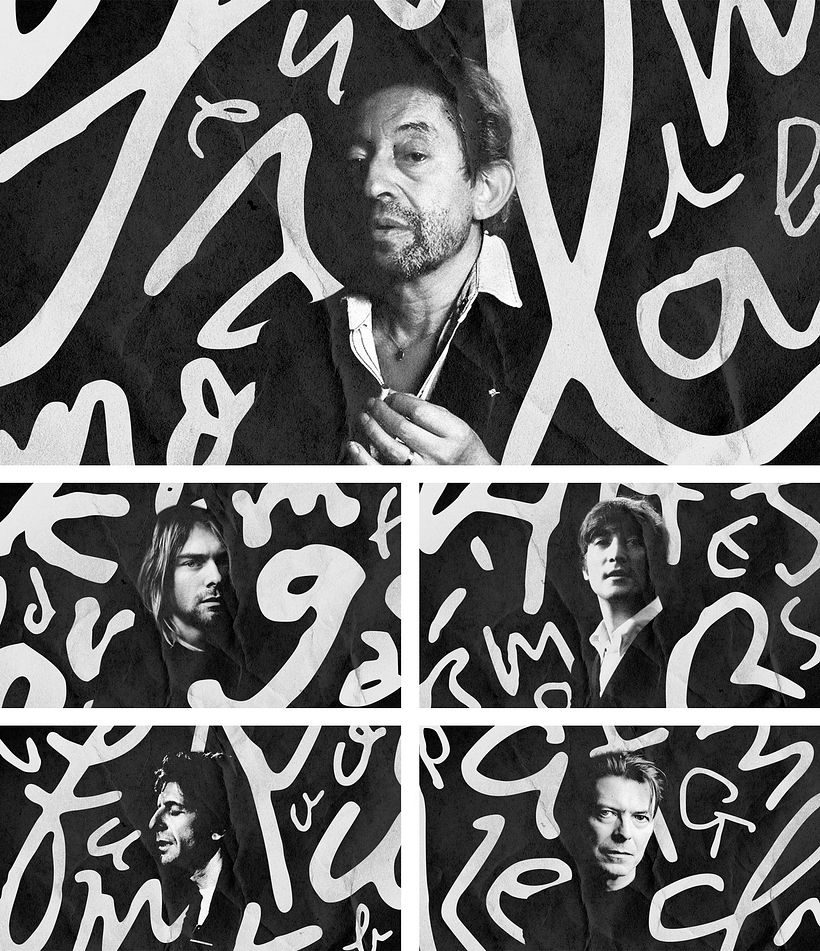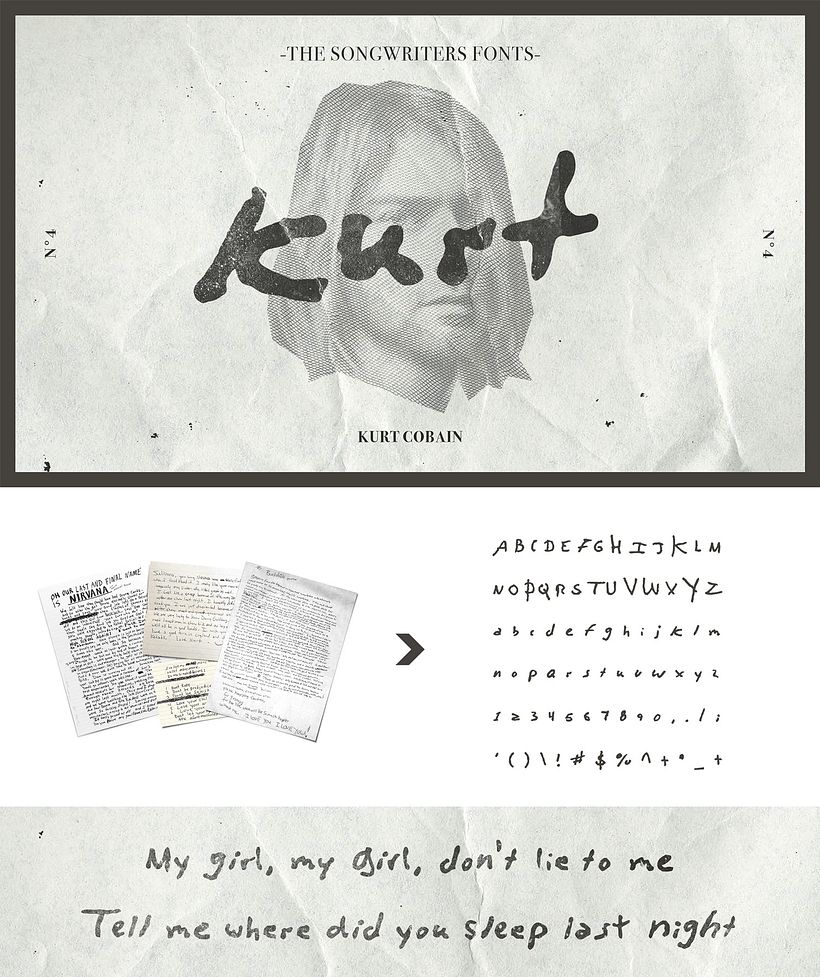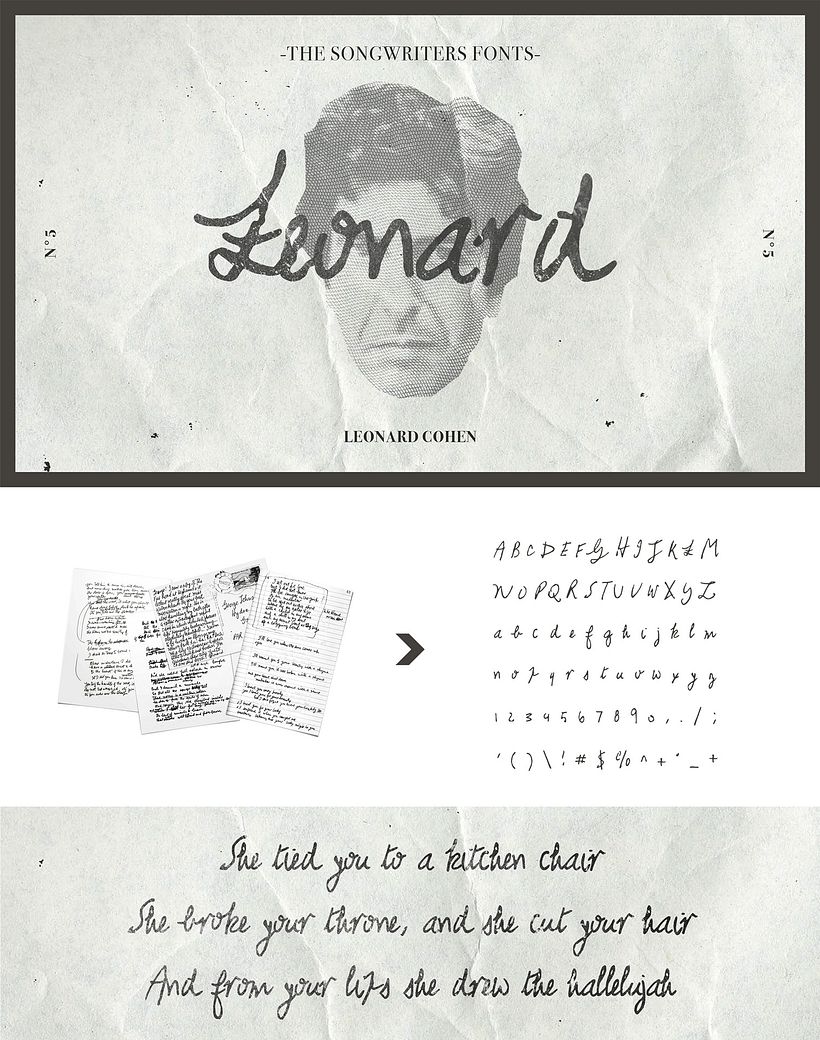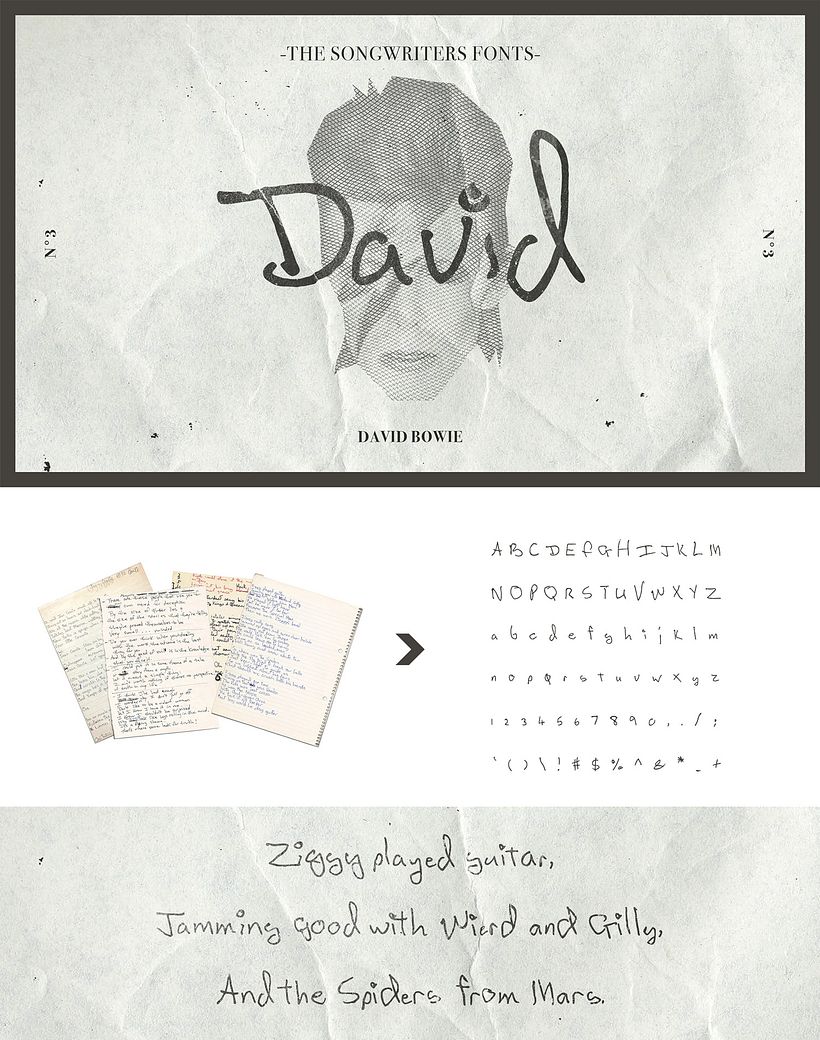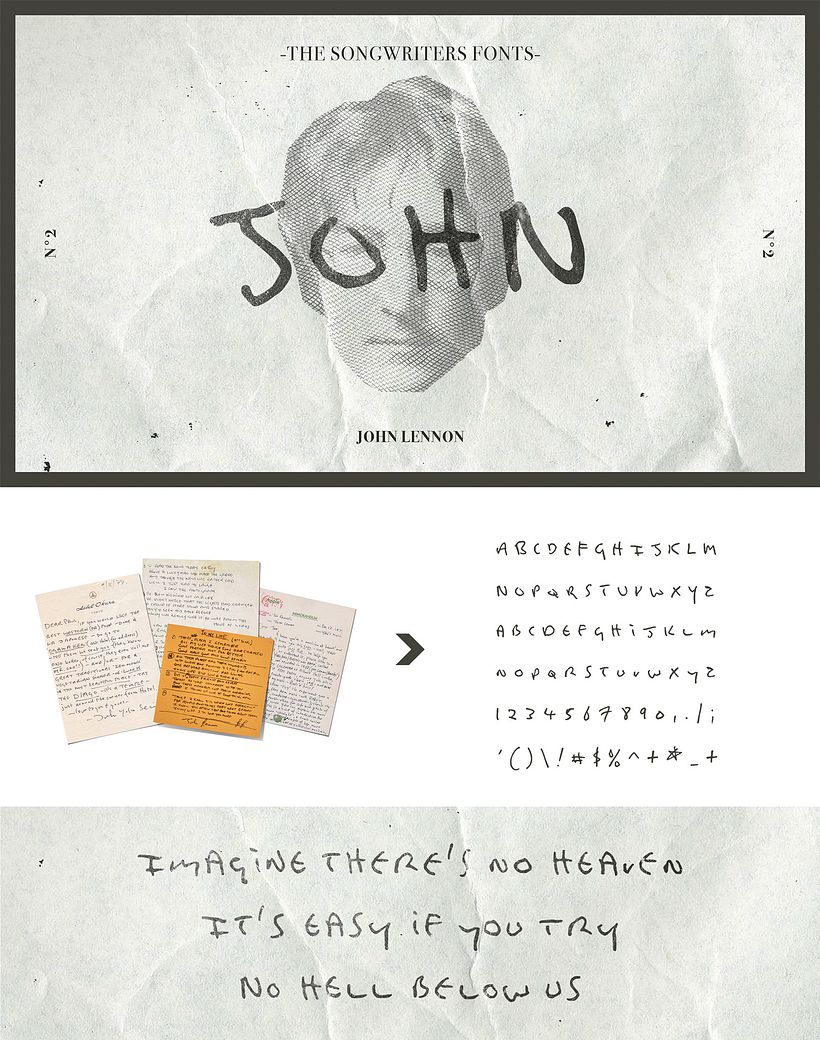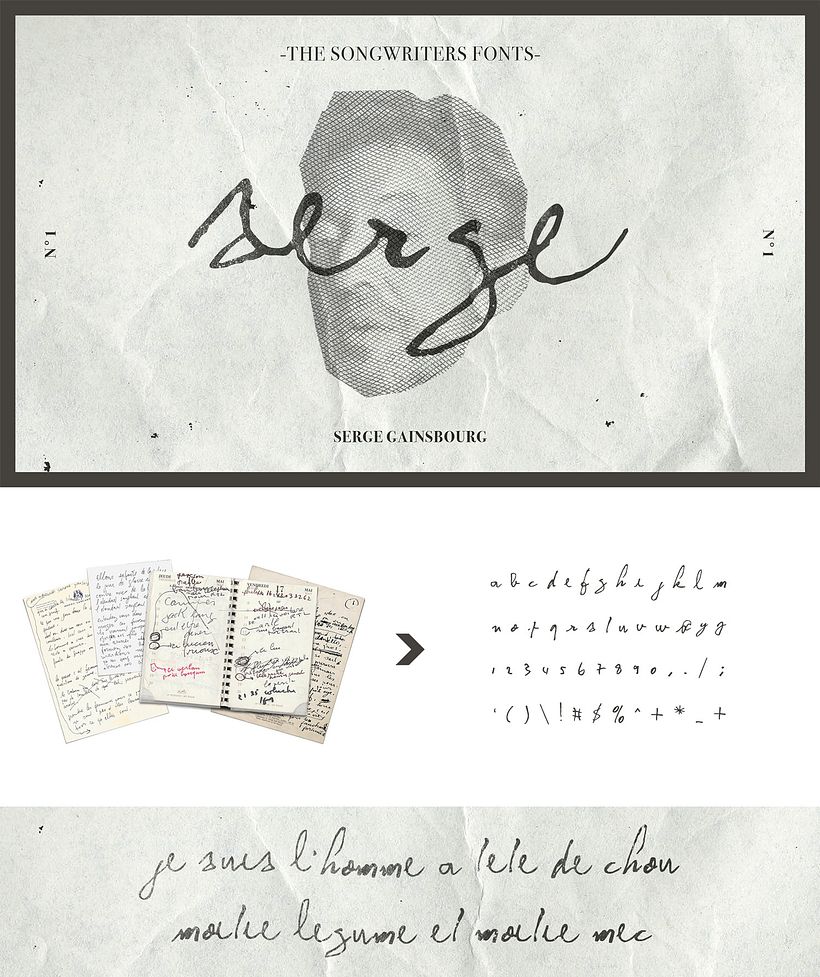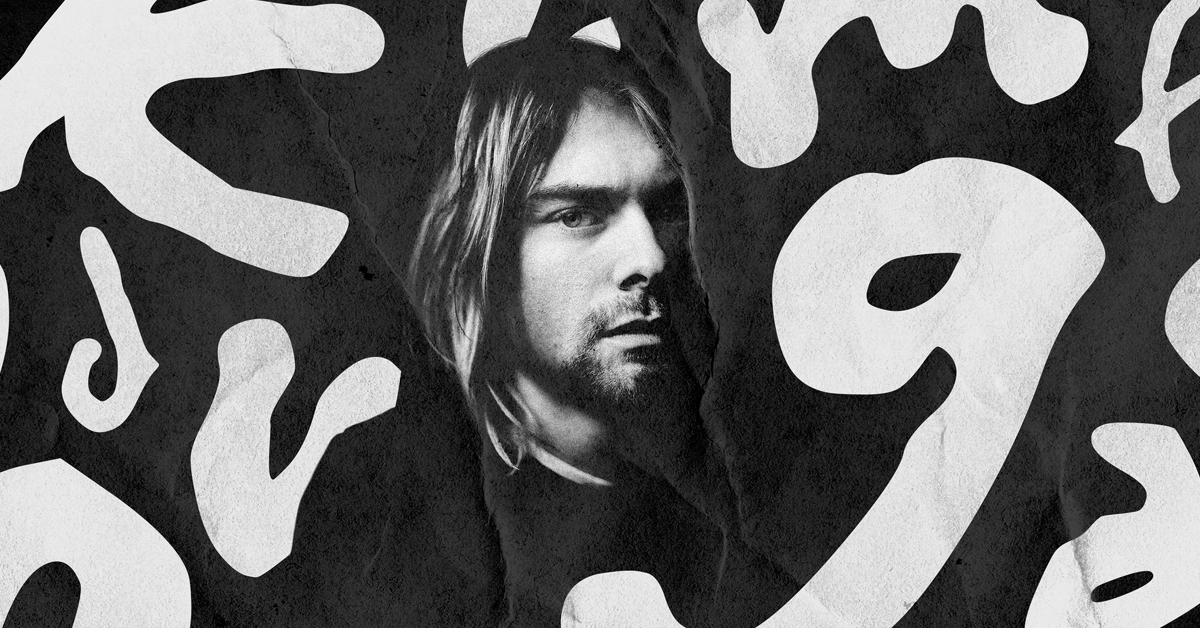
Songwriters fonts: tipografías caligráficas de tus músicos favoritos
Estas tipografías han sido diseñadas inspiradas por la caligrafía de tus músicos favoritos: Cobain, Bowie, Lennon...
La música y el diseño son elementos prácticamente indisolubles. Son pocos los creativos que no encuentren en la música una fuente de inspiración infinita y que puede materializarse de multitud de maneras diversas. El diseñador francés Nicolas Damiens, por ejemplo, se basó en la escritura de algunos de los músicos más célebres de las últimas décadas para crear Songwriters fonts, una serie de tipografías diseñadas a partir de la escritura de artistas como Kurt Cobain, John Lennon, David Bowie, Serge Gainsbourg o Leonard Cohen.
Estudiando las letras manuscritas de sus canciones, cartas, anotaciones personales e incluso la nota de suicido del líder de Nirvana, Damiens ha diseñado cinco tipografías, bautizadas según el nombre de los autores originales de sus formas, que pretenden continuar con el legado inspiracional que la música siempre ha llevado sobre sus hombros. Pero también para devolverle a la música ese gran favor que hace a la creatividad, ya que estas fuentes han sido creadas para inspirar a otros músicos a la hora de escribir sus propias composiciones.
Estas tipografías, además de su vertiente pragmática y servirnos como inspiración, nos permiten fijarnos en características de su manera de escribir, ayudándonos a conocer un poco más acerca la personalidad de estos artistas que, con su música y sus letras han marcado a generaciones enteras.